10 Font Graffiti Terbaik Download Gratis
10 Font Graffiti Terbaik Download Gratis untuk anda pecinta dunia graffiti bisa menggunakan beberapa font ini untuk menciptakan desain graffiti anda yang mengagumkan. Beberapa font dibawah ini adalah font pilihan yang sudah di download jutaan orang yang mencintai dunia graffiti.
1. The Graffiti Font
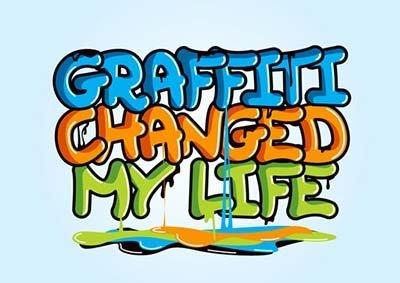
Font graffiti terbaik buatan tangan ini diciptakan oleh desainer grafis 27 tahun Mike Karolos yang saat ini bekerja sebagai art director di Athena. Warna berani dan segar, funky merasa font graffiti gratis ini membuatnya sempurna untuk menyuntikkan kehidupan untuk setiap dinding kosong. Hanya huruf besar yang tersedia, tetapi font gratis ini baik untuk penggunaan pribadi dan komersial.
2. Brooklyn
Salah satu gaya font graffiti terbaik dan favorit, Brooklyn dikembangkan oleh desainer grafis Paul Reis, yang menggambarkan secara online sebagai ‘jenis huruf berbasis kaligrafi yang bersifat ramping dan brutal’. Dibuat sebagai hasil dari latihan kaligrafi dan corat-coret, Brooklyn tersedia dalam dua versi, reguler dan inline.
3. Misdemeanour
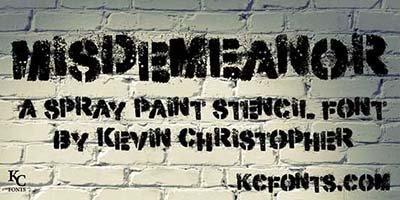
Misdemeanour adalah font graffiti terbaik yang bernama spraypaint stensil diciptakan oleh Kevin Christopher. Gratis untuk penggunaan pribadi saja, ini bisa menjadi font graffiti yang sempurna untuk Anda. font ini terinspirasi desain Banksy.
4. You Murderer
Ingin menyampaikan getaran gila? Kemudian Murder font yang cukup jelas menawarkan font graffiti terbaik sesuai psikotik bagi Anda untuk dicoba. Dibuat oleh Nate Piekos, gratis untuk penggunaan pribadi saja.
5. Amsterdam Graffiti
Designer Jesse Kuiper adalah otak di balik brilian font graffiti terbaik dan font gratis. Sebuah pilihan populer, font ini hampir 1.4million download sejak dirilis. Ini gratis untuk penggunaan pribadi saja, dengan sumbangan kepada penulis, seperti biasa, selamat datang.
6. Urban Jungle
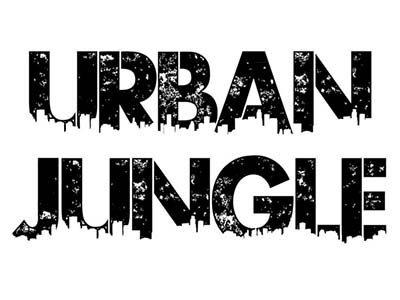
Font Ini besar, jenis huruf ‘Perkotaan Jungle’ diciptakan oleh desainer Kevin Christopher KC Font. Free Font graffiti yang eye-catching sangat cocok untuk membuat poster dan selebaran yang menonjol dengan gaya graffiti. Ada biaya untuk mendapatkan font penuh tetapi Anda dapat melakukan pekerjaan pribadi untuk isi hati Anda dengan versi demo gratis.
7. Nosegrind
Ini huruf graffiti bebas berasal dari Scriptorium Font, dibuat oleh desainer game, editor dan sejarawan Dave Nalle. Menggambarkan tipografi, Nalle mengatakan pada situs web-nya, ‘Nosegrind didasarkan pada graffiti budaya skateboard yang dikumpulkan dari berbagai sampel gaya serupa yang ditemukan di dinding Austin maupun online.
8. The Pricks
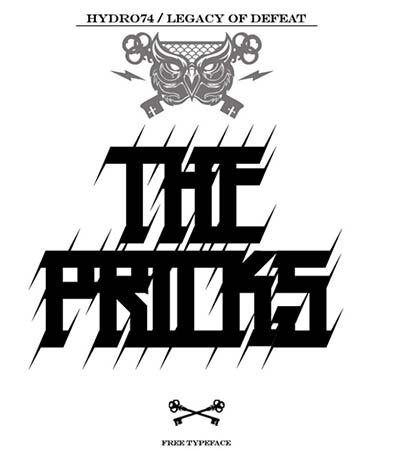
Font yang sederhana dengan bentuk paku dibuat oleh desainer Orlando berbasis Hydro74 alias Joshua M. Smith. Font graffiti gratis hanyalah salah satu dari banyak tipografi Hydro74. Sementara banyak dari font mereka yang Anda harus membayar, desainer yang terkenal murah hati juga memiliki banyak font gratis yang brilian untuk diperebutkan di situsnya.
9. Degrassi
Degrassi typeface pencipta Ray Larabie menggambarkan huruf graffiti gratis ini sebagai ‘agak Wack, graffiti terinspirasi huruf’, yang cukup banyak meringkas itu. Presiden perusahaan Jepang Typodermic Font, Larabie telah merancang berbagai tipografi, banyak yang bebas untuk men-download di situs nya.
10. Brock Vandalo
Mahasiswa desain grafis Luis Marques alias Brock Marques adalah orang di balik huruf graffiti gratis ini. Fitur desain bulat berbentuk karakter dengan ujung tipis dan tikungan hairpin. Marques menjelaskan jenis huruf nya sebagai ‘gembira dan kadang-kadang tidak terorganisir tapi dengan rasa urban coretan graffiti’.